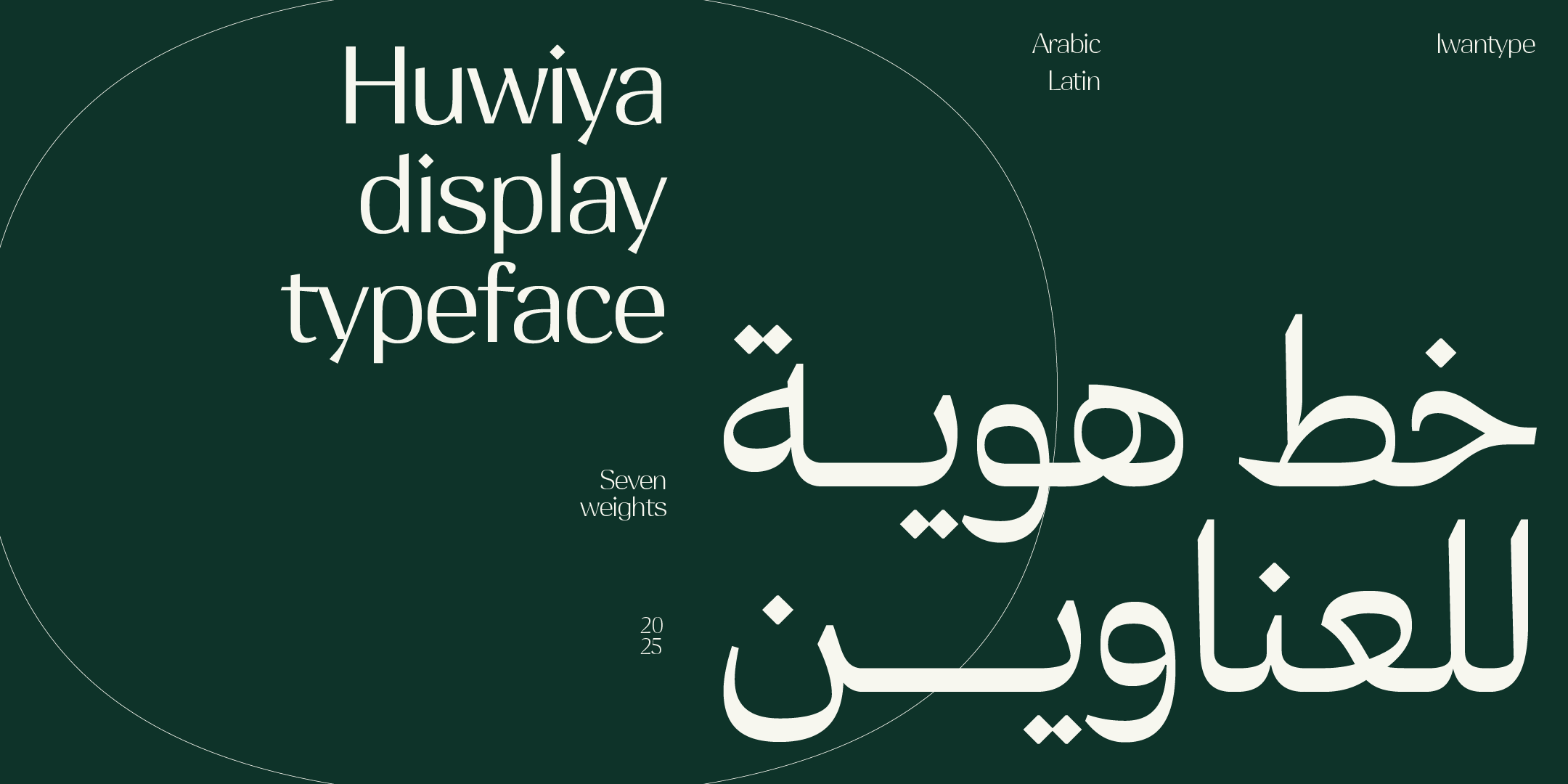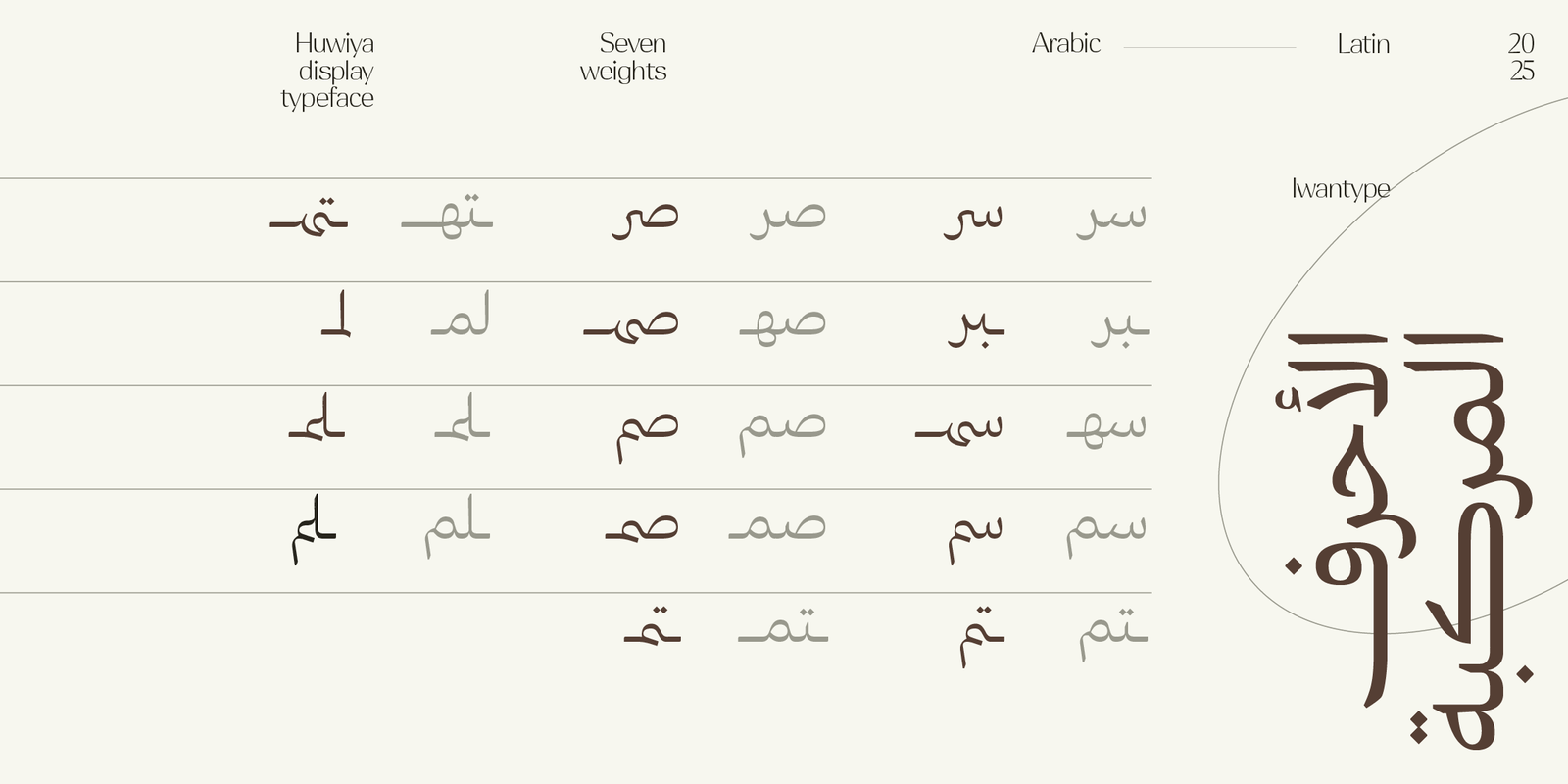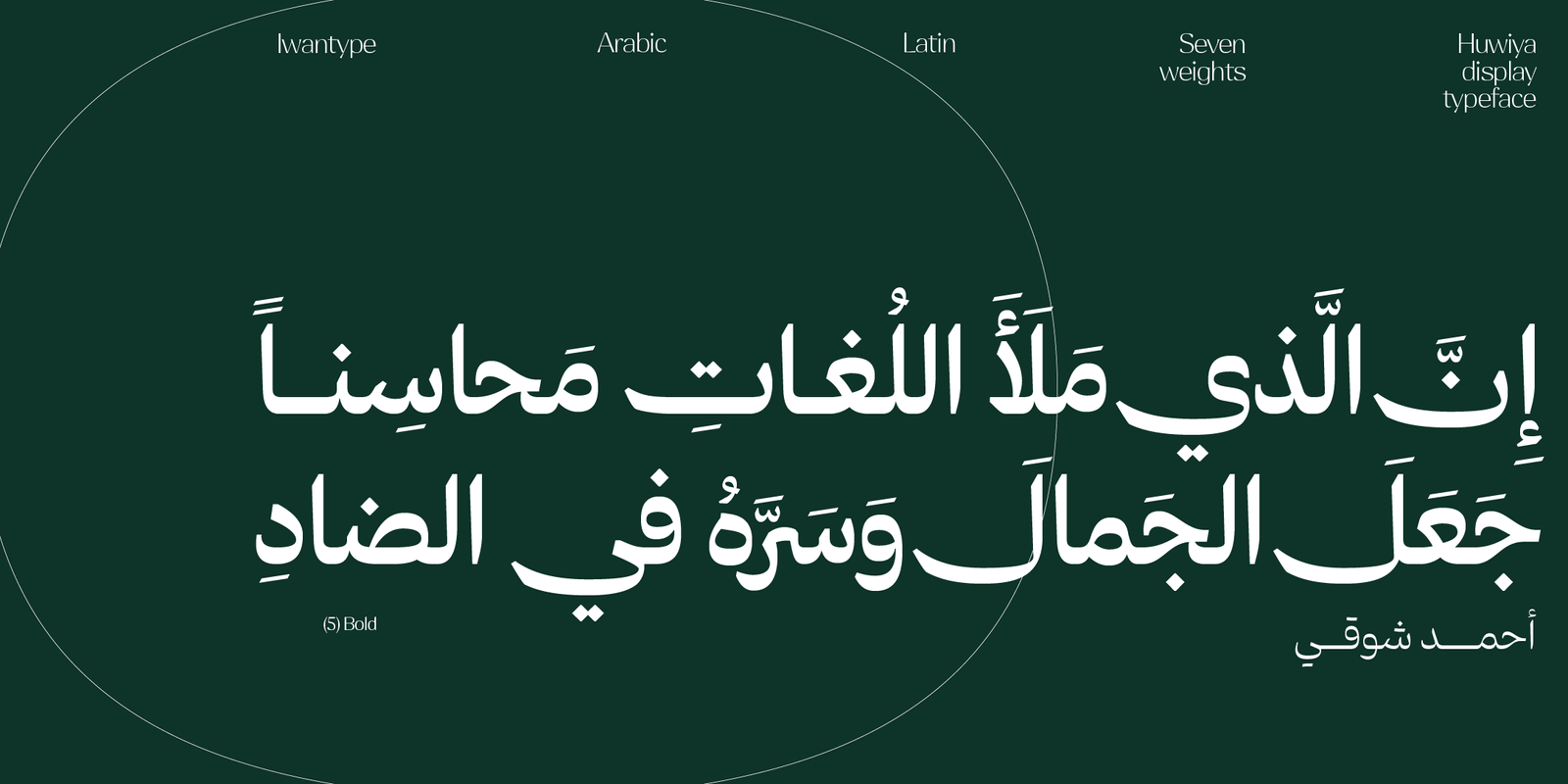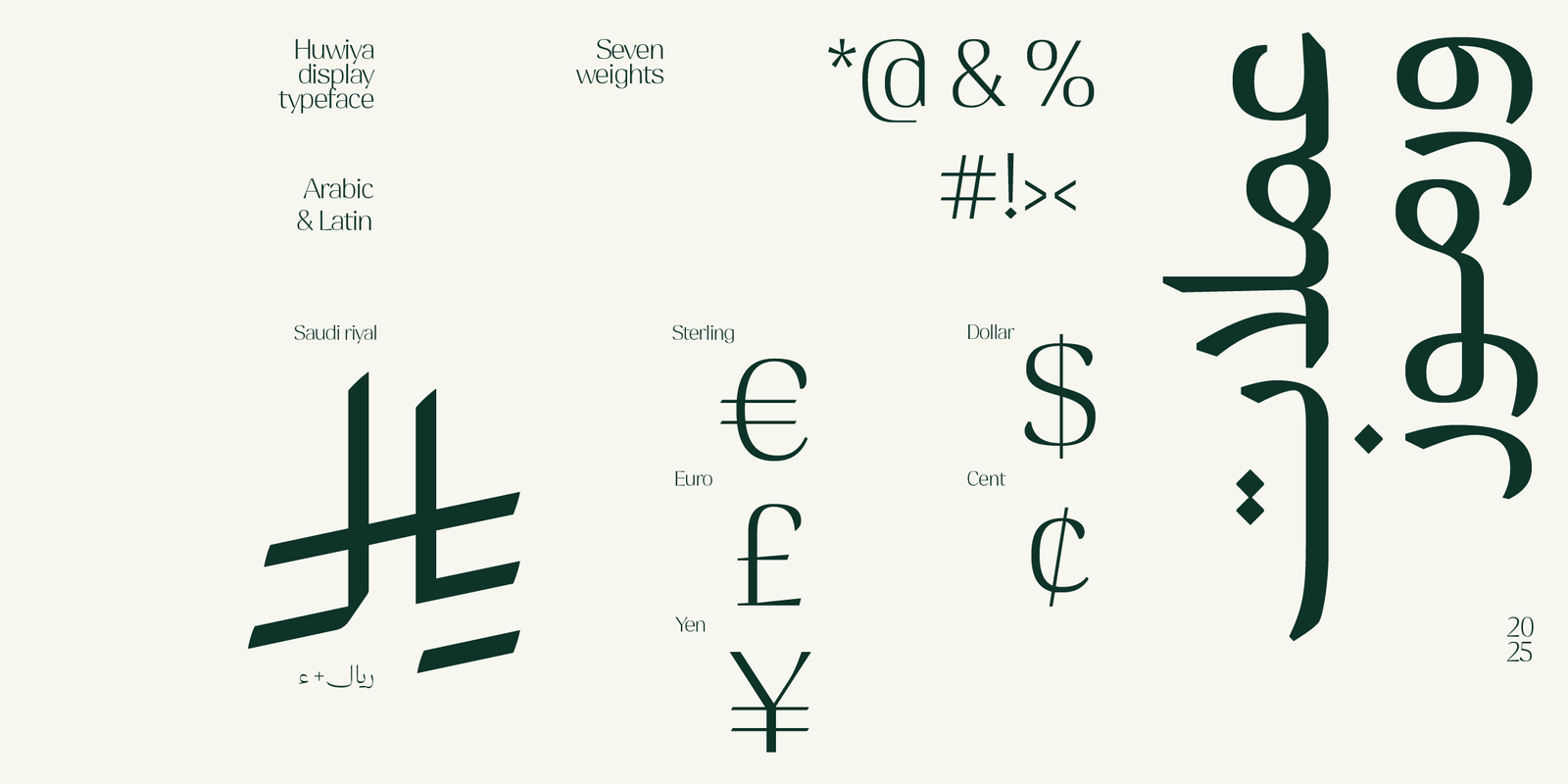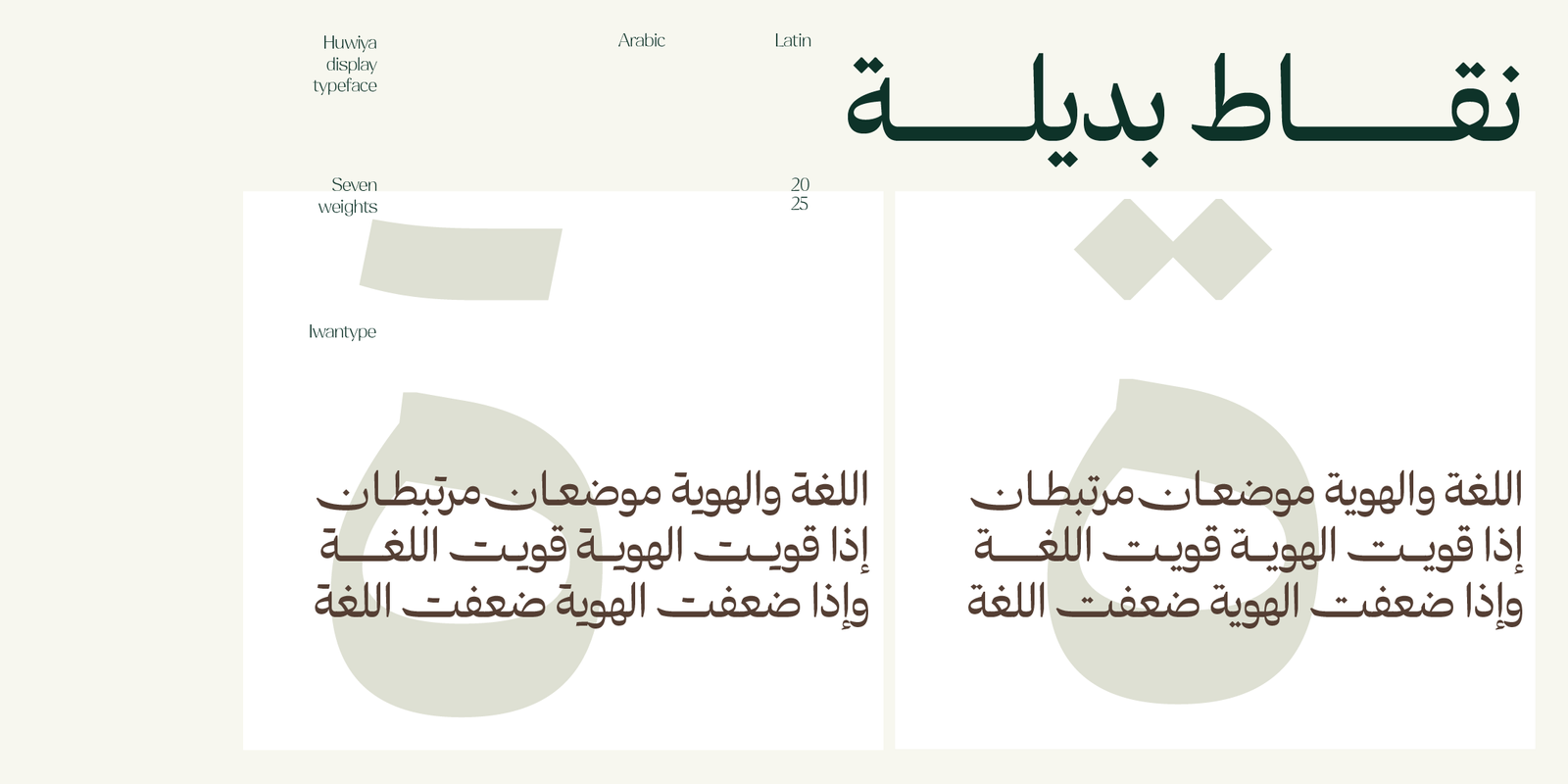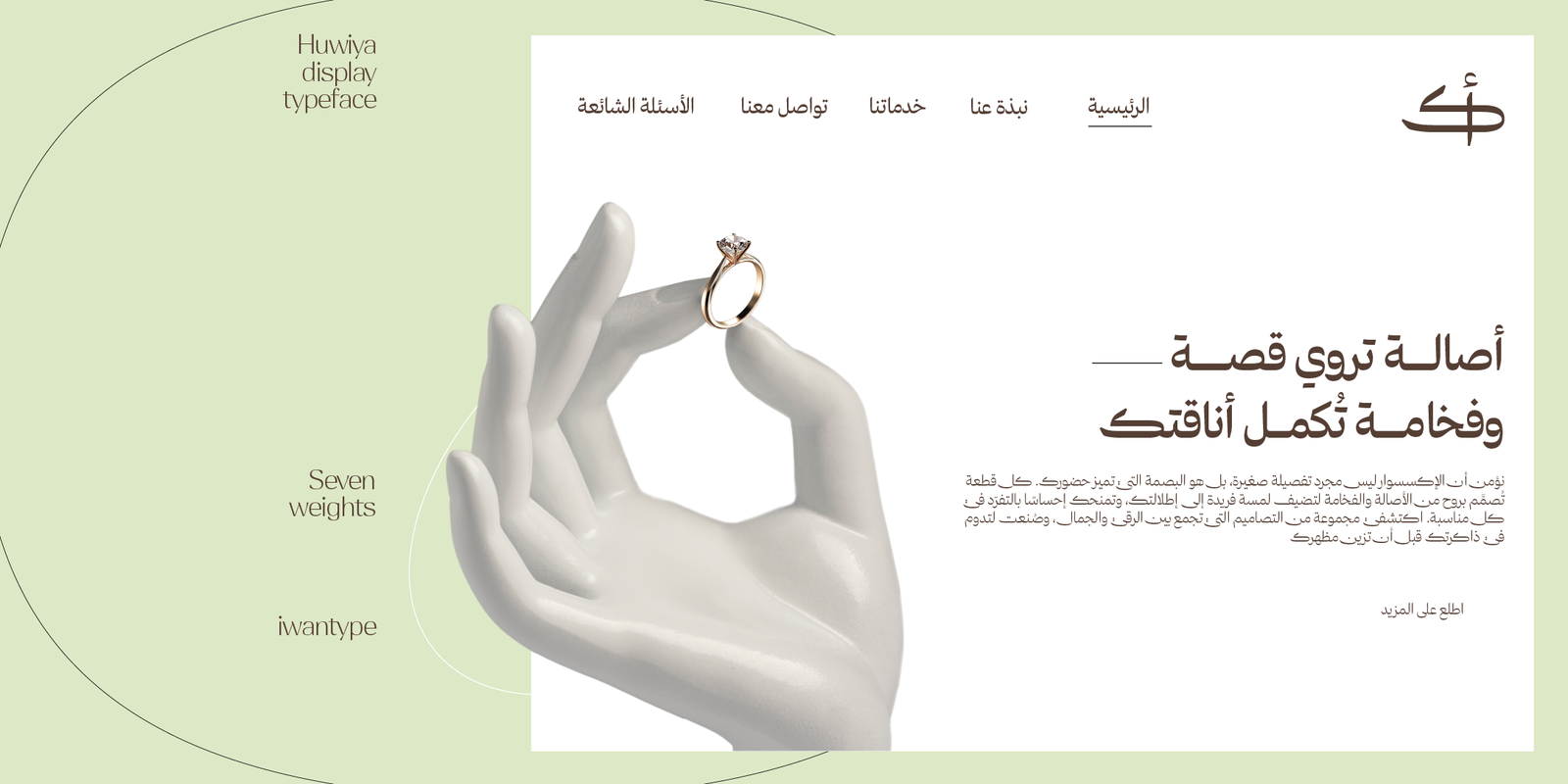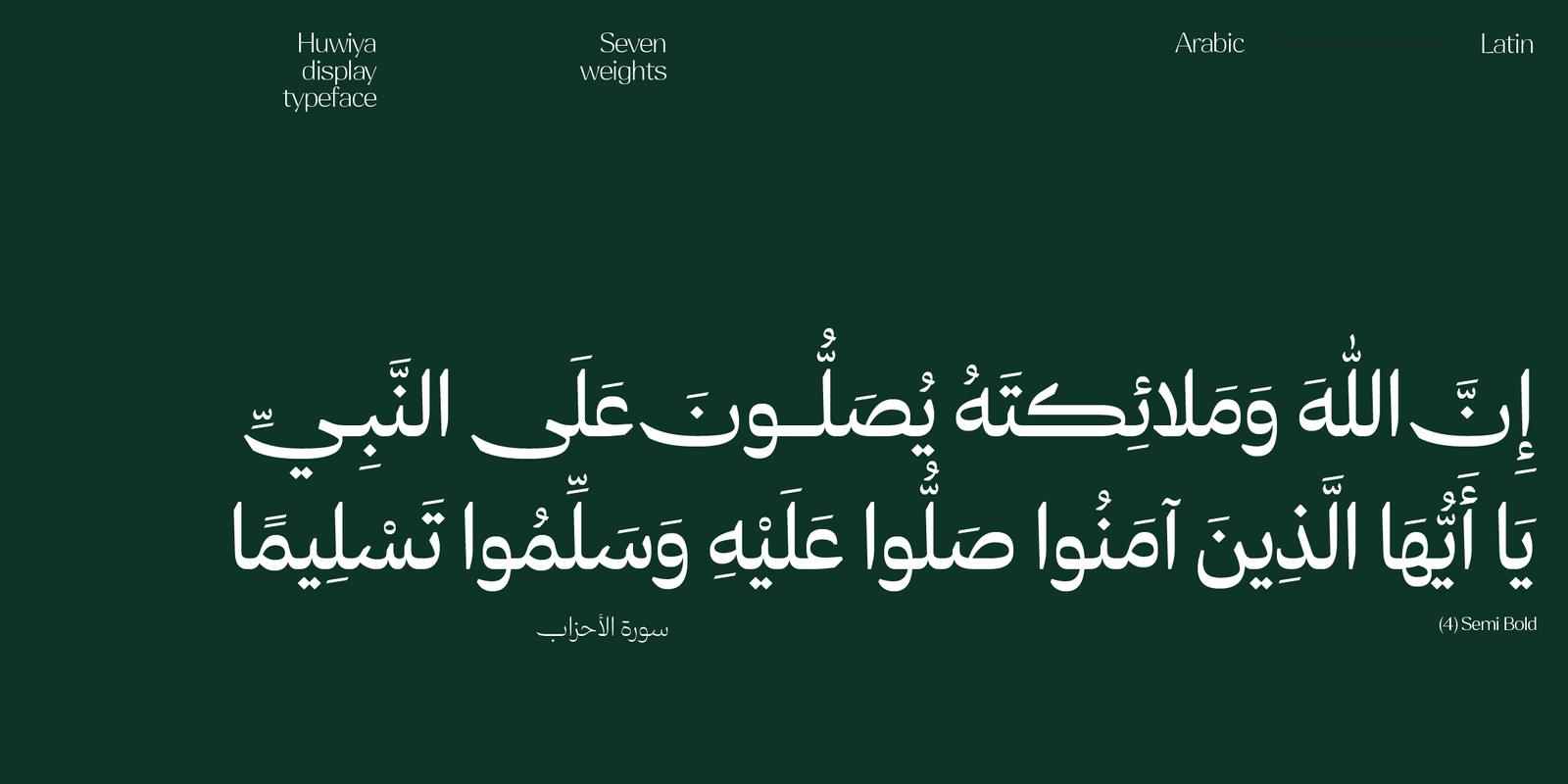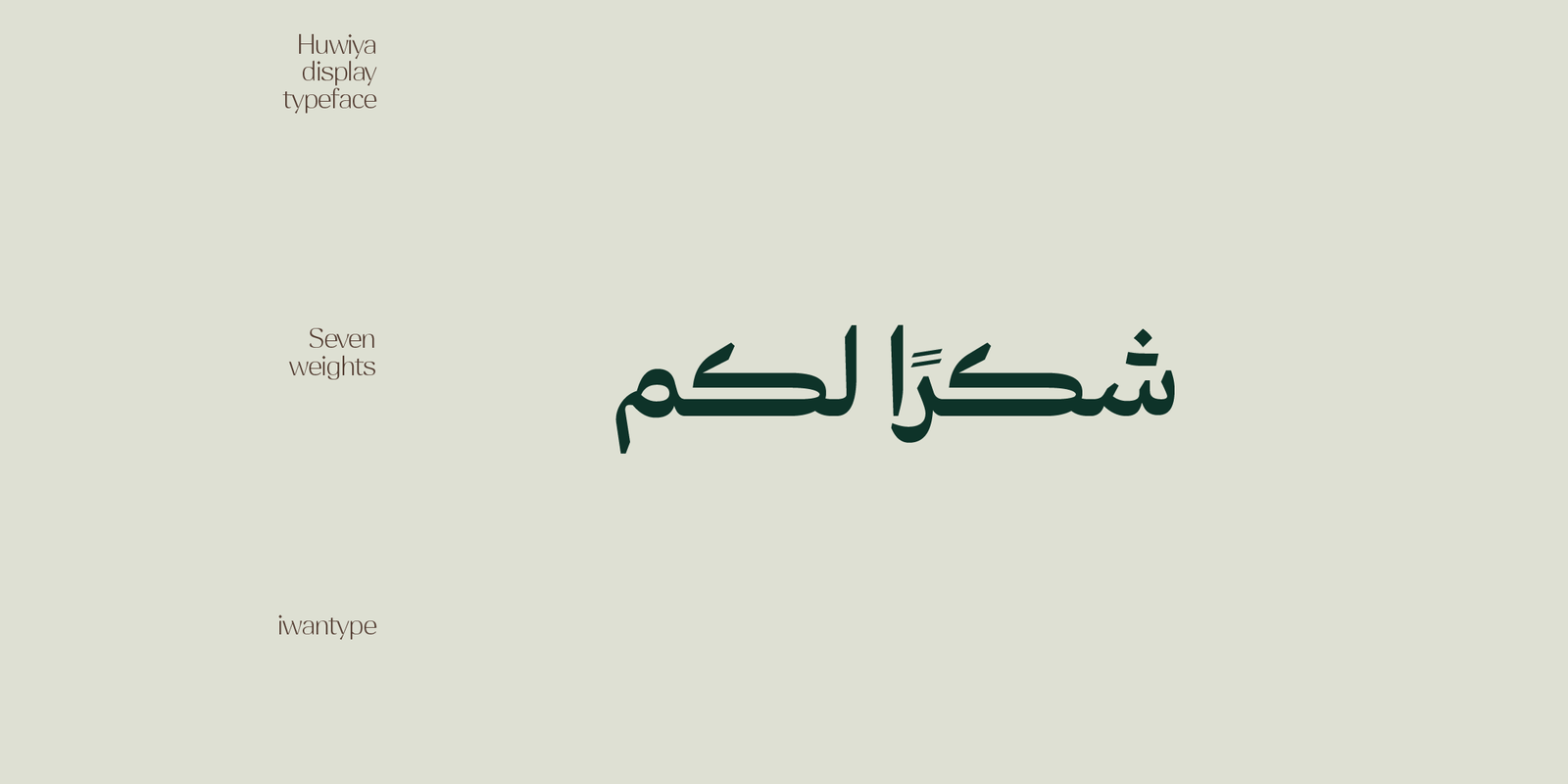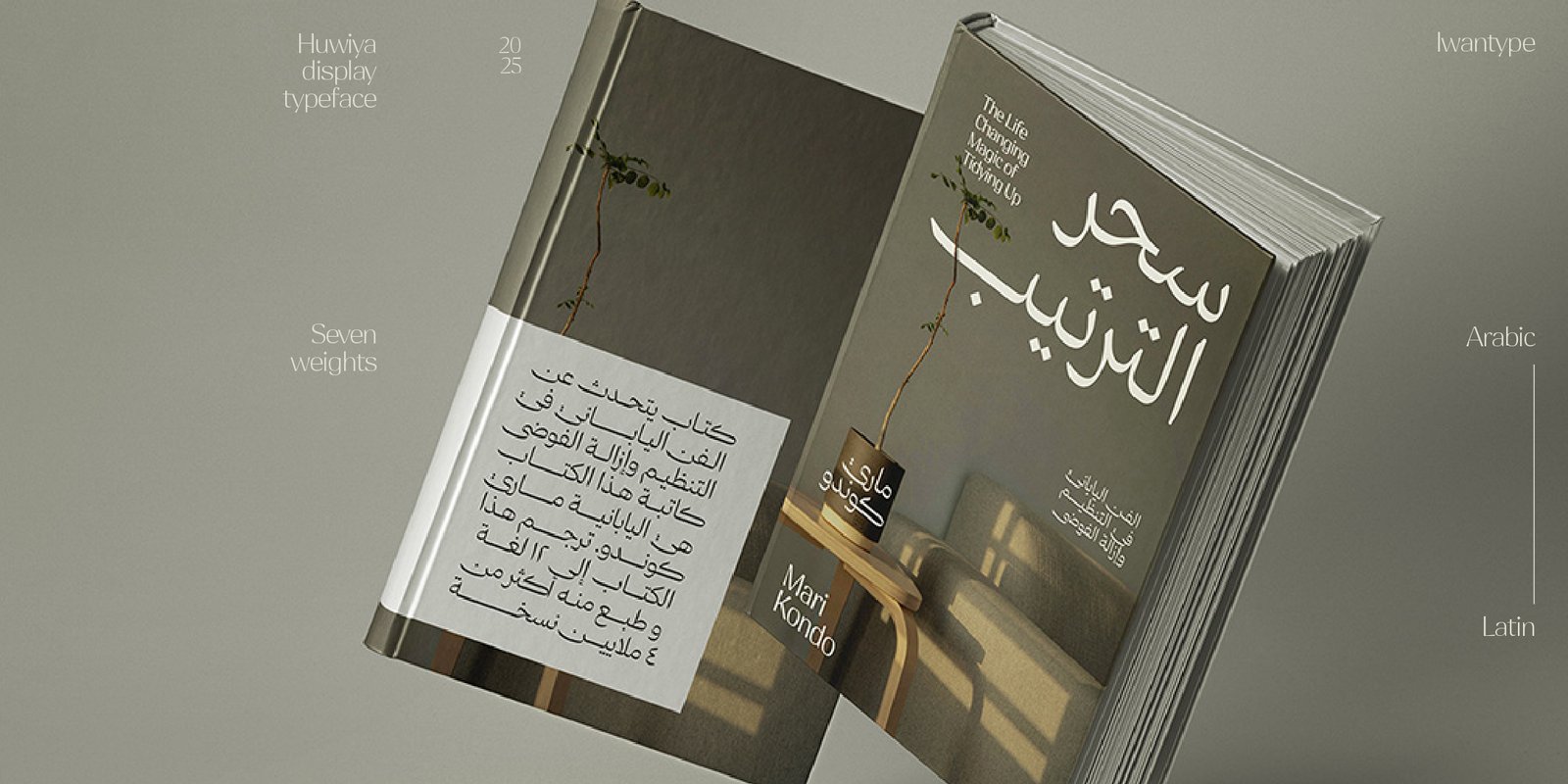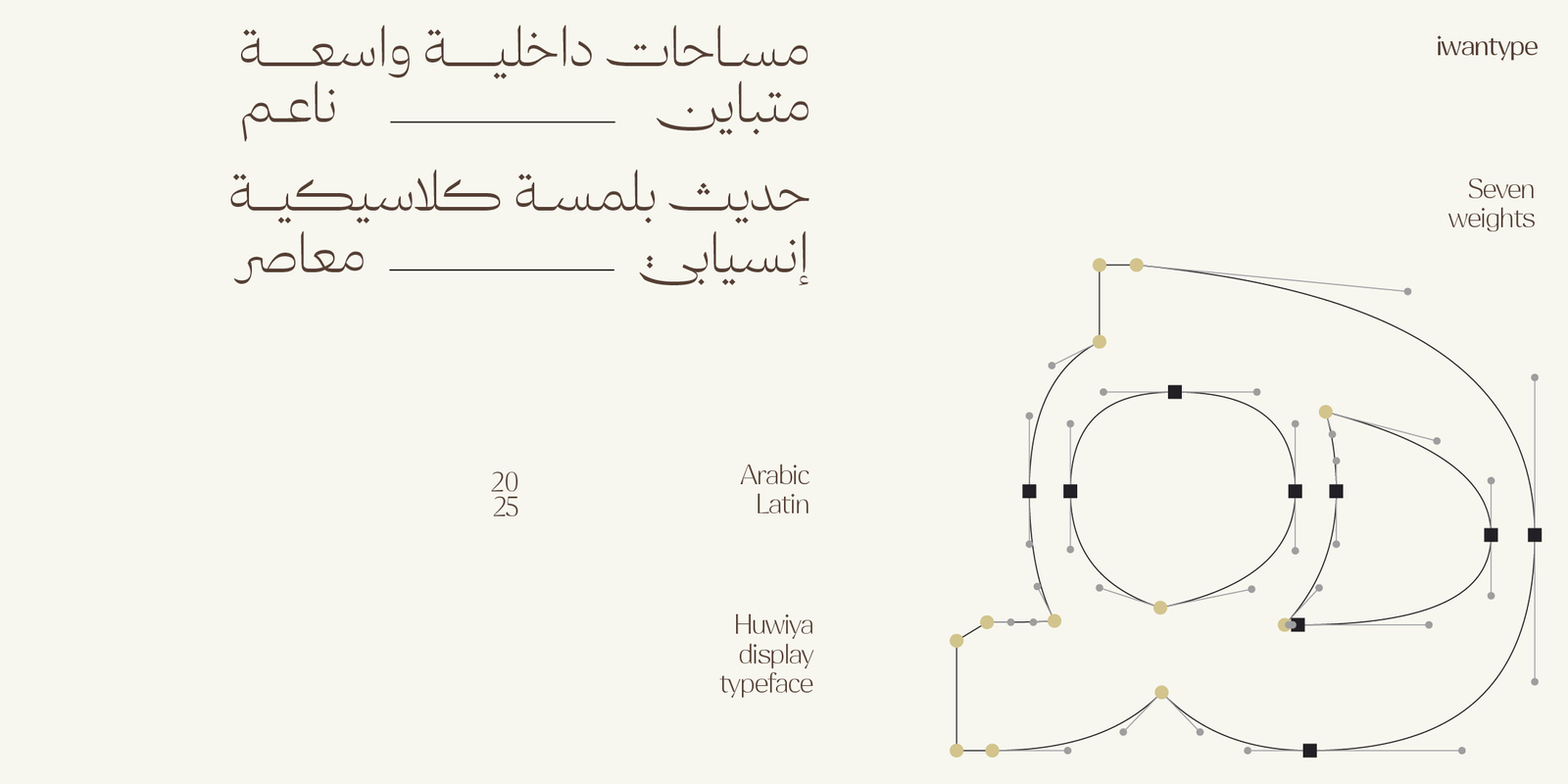
خط هوية للعناوين- Huwiya Display : الأناقة الهادئة والتصميم العصري
اكتشف خط “هوية للعناوين”، الخط العربي واللاتيني الذي يعيد تعريف الفخامة الحديثة. بفضل تصميمه الفريد الذي يجمع بين المنحنيات الهندسية الناعمة والخطوط الهادئة،
يمنحك “هوية للعناوين” توازناً مثالياً بين القوة والهدوء. هو ليس مجرد خط، بل هو لمسة فنية تضفي على مشاريعك طابعاً بصرياً فريداً لا يُنسى.
مميزات خط هوية للعناوين:
يتضمن الخط العديد من مزايا OpenType التي تضفي عليه مرونة وتنوعًا في الاستخدام، مثل:
- أحرف مرسلة (تُفعَّل بإضافة “ءء” بعد الحرف)
- حرف ياء بنزول أقل: يقلل من نزول السطر، مما يعزز من انتظام النصوص.
- أحرف المركبة: تسهم في تحسين المظهر العام للنص وتزيد من سلاسته.
- نقاط بديلة
- يدعم رمز الريال السعودي، ويمكن تفعيله بإضافة حرف “ء” بعد كتابة كلمة “ريال”.
اللغات: العربية والانجليزية
الاوزان : ٧ اوزان